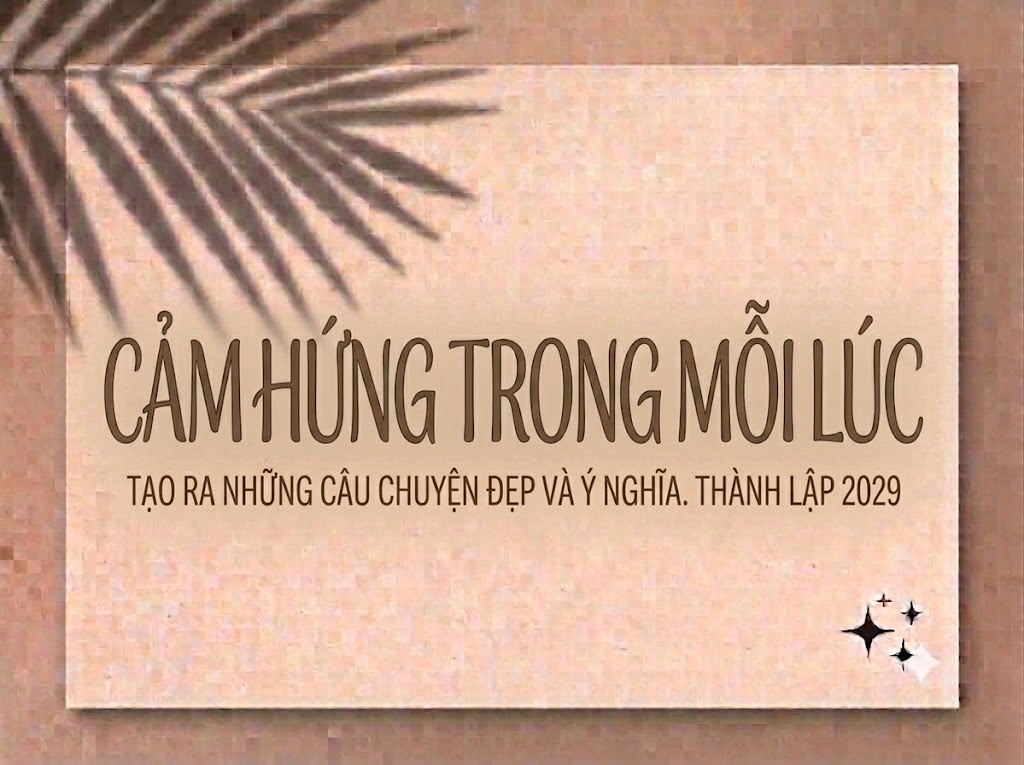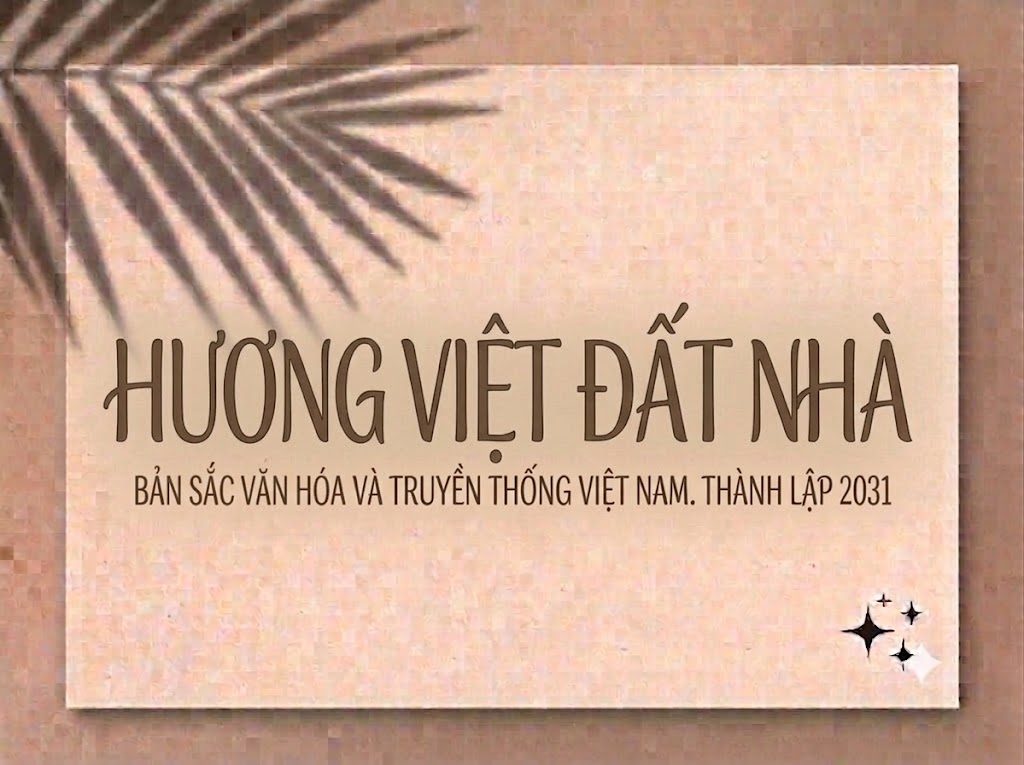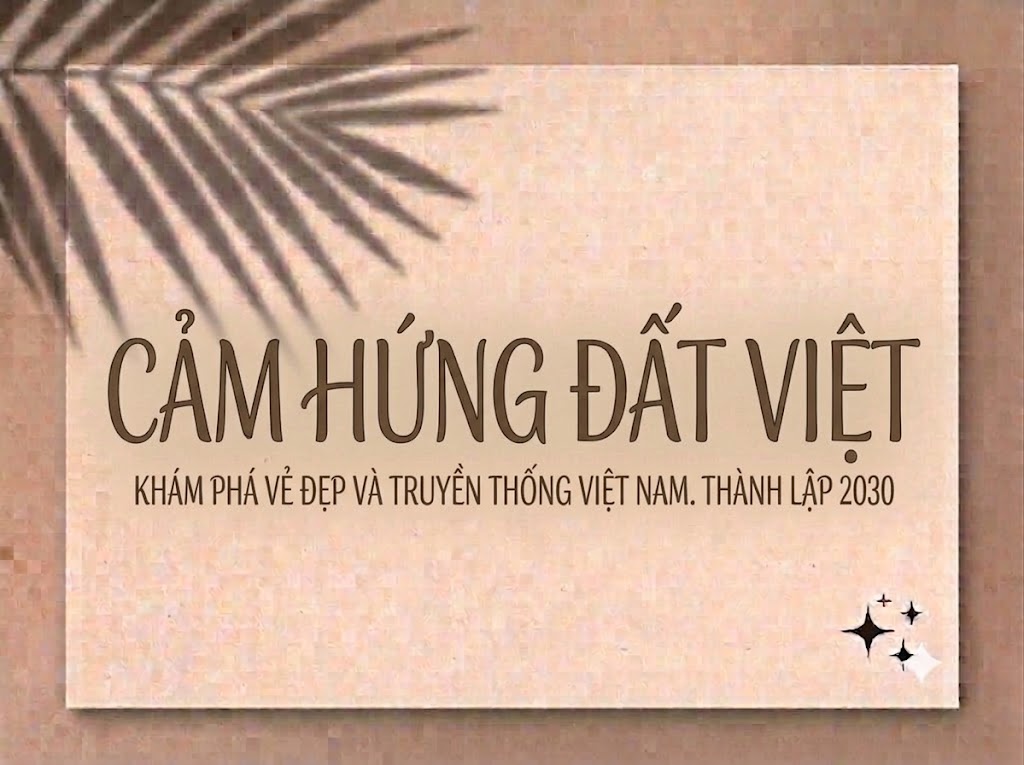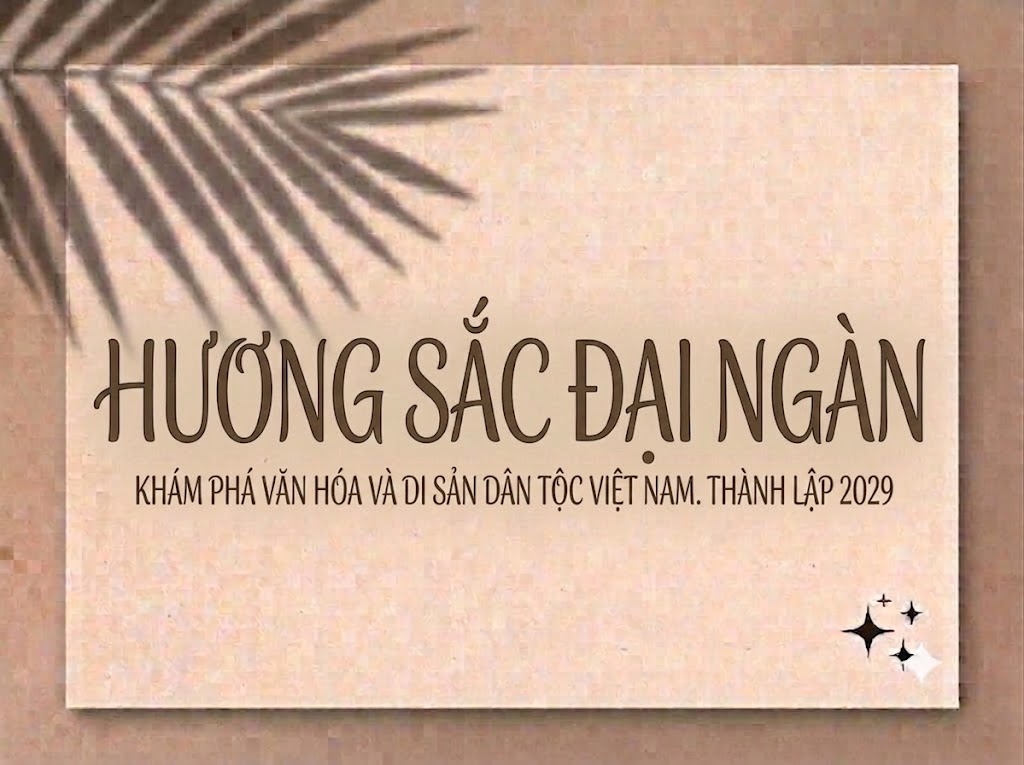
1FTV VIP Amoera
Trong phân khúc thiết kế cao cấp đòi hỏi tính thẩm mỹ, chiều sâu và sự xa xỉ, các phông chữ có chân (Serif) dáng mảnh luôn là sự lựa chọn hàng đầu của các nhà sáng tạo. Một bộ chữ sở hữu tỷ lệ hình học cao ráo kết hợp cùng các đường nét uốn lượn điệu nghệ sẽ ngay lập tức thổi hồn vào tác phẩm, biến những dòng tiêu đề thông thường trở thành một kiệt tác nghệ thuật đầy kiêu sa.
Nếu bạn đang tìm kiếm một giải pháp typographic thời thượng, mang hơi hướng quý tộc để nâng tầm nhận diện thương hiệu, làm ảnh bìa thu hút hay tạo điểm nhấn cho các thước phim cinematic, thì font 1FTV VIP Amoera chính là câu trả lời lý tưởng.
Giới thiệu về font 1FTV VIP Amoera
Font 1FTV VIP Amoera là một bộ chữ hiển thị có chân (serif display) mang phong cách tân cổ điển đầy quý phái, thanh lịch và hướng đến các tiêu chuẩn mỹ thuật cao cấp.
Tác phẩm này được hoàn thiện chỉn chu ngay ở phiên bản đầu tiên Version 1.000, đem lại kết cấu đường nét mượt mà và sự đồng bộ tuyệt đối giữa các ký tự khi phối chữ.
Được thực hiện và chia sẻ rộng rãi bởi đội ngũ 1FTV, đây là giải pháp typographic đỉnh cao cho các dự án truyền thông định vị phân khúc luxury tại Việt Nam.
Đặc điểm nổi bật của phong cách thiết kế VIP Amoera
Sức hút mê hoặc của font 1FTV VIP Amoera đến từ dáng chữ đứng cao ráo, thanh mảnh kết hợp tài tình với những đường biến điệu nghệ thuật đầy phóng khoáng:
Định dạng All-Caps độc đáo: Phông chữ được xây dựng theo cấu trúc viết hoa đồng bộ cho cả hai hàng ký tự trên hệ thống. Tiện ích này tạo ra sự nhất quán, cân bằng tuyệt đối về mặt cao độ và giúp các khối từ luôn ngay ngắn, vững chãi.
Nét uốn lượn mang tính biểu tượng: Điểm nhấn đắt giá của VIP Amoera nằm ở các đường cong lãng mạn được lồng ghép khéo léo vào các ký tự như Q, R, K, A. Chữ Q sở hữu phần đuôi hạ thấp uốn lượn kiêu sa, chữ R và K có phần chân vát cong mềm mại, trong khi thanh ngang của chữ A được cách điệu như một làn sóng mượt mà.
Độ tương phản tinh tế: Sự chênh lệch giữa nét thanh siêu mảnh và các điểm nhấn đậm vừa phải mang lại chiều sâu thị giác cực kỳ cuốn hút, gợi liên tưởng đến trang bìa của các tạp chí thời trang danh tiếng toàn cầu.
Để phông chữ vận hành hoàn hảo trên mọi hệ điều hành từ Windows đến macOS, phiên bản font 1FTV VIP Amoera đã trải qua quy trình xử lý thông số kỹ thuật nội tại vô cùng nghiêm ngặt:
Hệ thống khoảng cách chữ (kerning) và độ giãn dòng (tracking) đã được căn chỉnh chuẩn xác đến từng pixel, giúp các nét chữ mảnh khi đứng cạnh nhau luôn giữ được khoảng trống thẩm mỹ lý tưởng, tạo cảm giác vô cùng thông thoáng và dễ chịu cho mắt người đọc.
Tích hợp đầy đủ bộ chữ cái viết hoa đồng bộ, dãy chữ số từ 0-9 dáng đứng thanh lịch cùng hệ thống các ký tự đặc biệt, dấu câu thông dụng (
1234567890.:,;'"(!?)+-*/=). -
Bản Việt hóa chuẩn chỉnh giúp các nhà sáng tạo nội dung hoàn toàn yên tâm thiết kế các văn bản tiếng Việt có dấu mà không lo gặp phải tình trạng nhảy font hay lỗi hiển thị ký tự.
Hình ảnh demo thực tế của font 1FTV VIP Amoera
Kích thước nhỏ (12pt – 24pt): Dù sở hữu các đường nét thanh mảnh, cấu trúc chữ đứng và các dấu tiếng Việt vẫn hiển thị rất rõ ràng, ngay ngắn, tạo trải nghiệm đọc mượt mà trên các giao diện hiển thị.
Kích thước lớn (36pt – 72pt): Đây là đất diễn hoàn hảo nhất để font chữ phô diễn toàn bộ sự kiêu sa, quý phái của các đường nét uốn lượn cách điệu, tạo hiệu ứng thị giác đỉnh cao chiếm trọn sự chú ý cho các dòng headline chính.
Ứng dụng của font VIP Amoera trong thiết kế đồ họa và làm video
Sở hữu nét cá tính sang trọng, quý phái và cấu trúc hình khối hoa đồng bộ tinh tế, font 1FTV VIP Amoera mở ra không gian ứng dụng vô cùng rộng lớn cho các dự án truyền thông và nội dung số:
Làm tiêu đề cho video ngắn (TikTok, Reels, Shorts): Kiểu chữ serif thanh lịch này cực kỳ ăn nhập với các video dạng cinematic, vlog phong cách sống, thời trang, lookbook hoặc quảng cáo sản phẩm cao cấp. Dáng chữ đứng cao ráo giúp các từ khóa chính giật tít hiển thị vô cùng nổi bật, tự nhiên trên các khung hình đứng 9:16 của thiết bị di động mà không che mất chủ thể.
Thiết kế ảnh thu nhỏ mạng xã hội (Thumbnail): Đây là vũ khí tuyệt vời để tạo nên những chiếc thumbnail YouTube, TikTok mang tính nghệ thuật, cao cấp cho các kênh thuộc chủ đề phong cách sống, làm đẹp, trang sức, e-commerce thời trang hoặc chia sẻ kiến thức chuyên sâu nhằm tăng tỷ lệ nhấp chuột nhờ giao diện chuyên nghiệp.